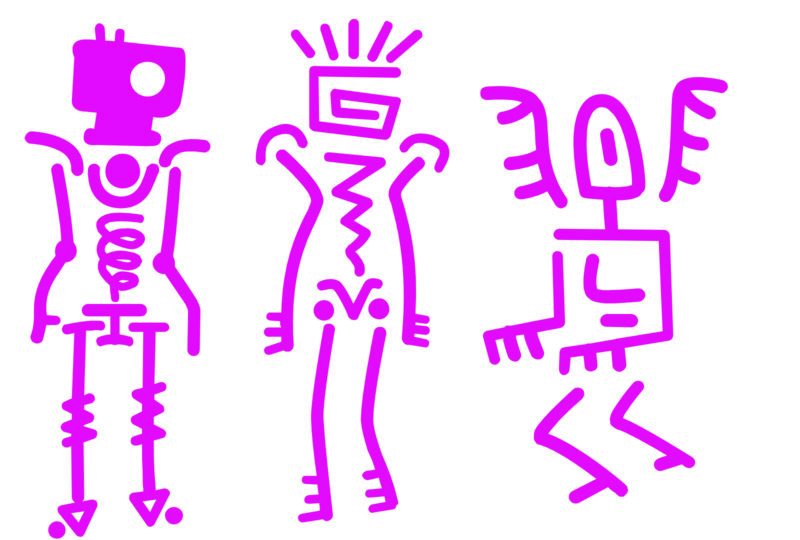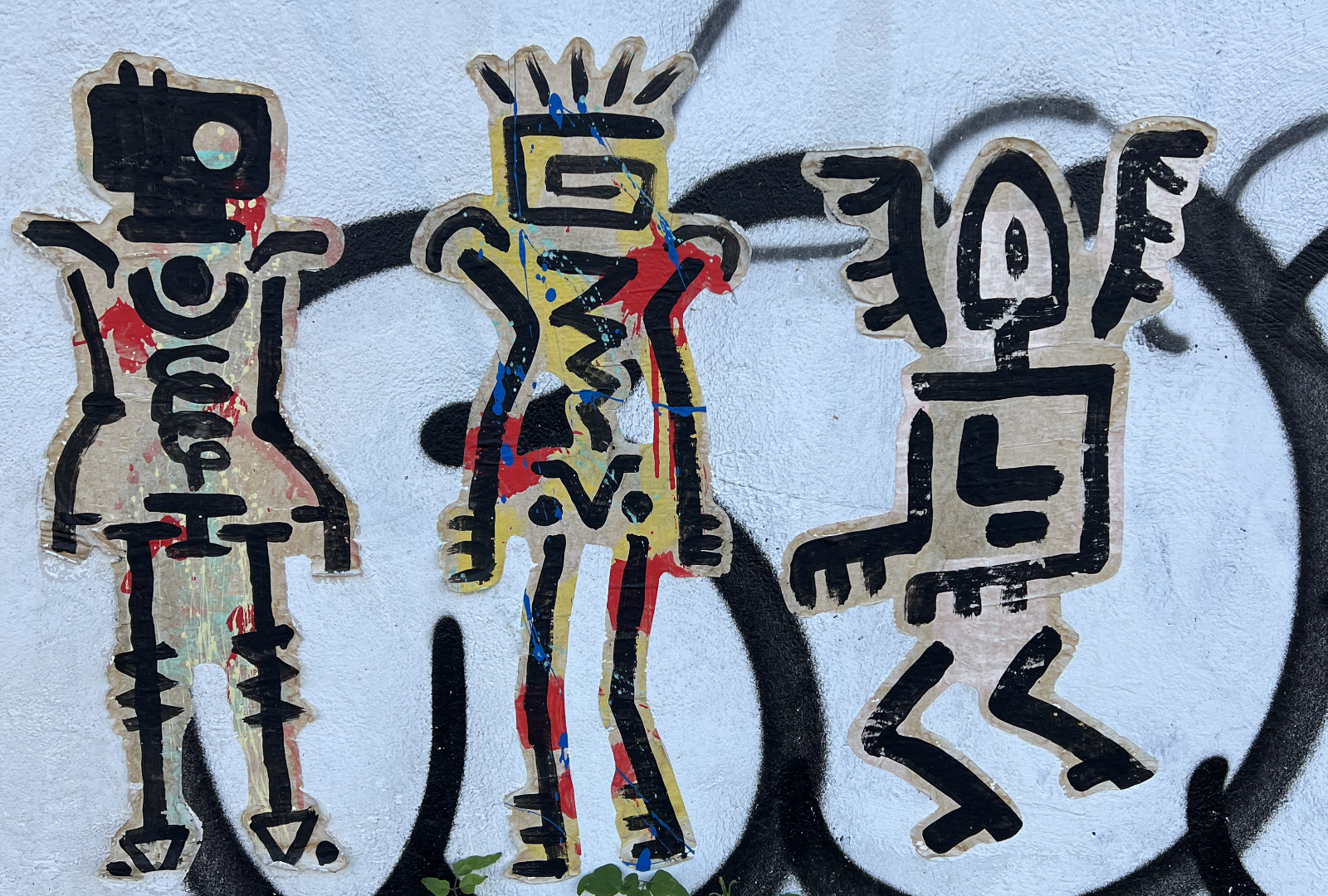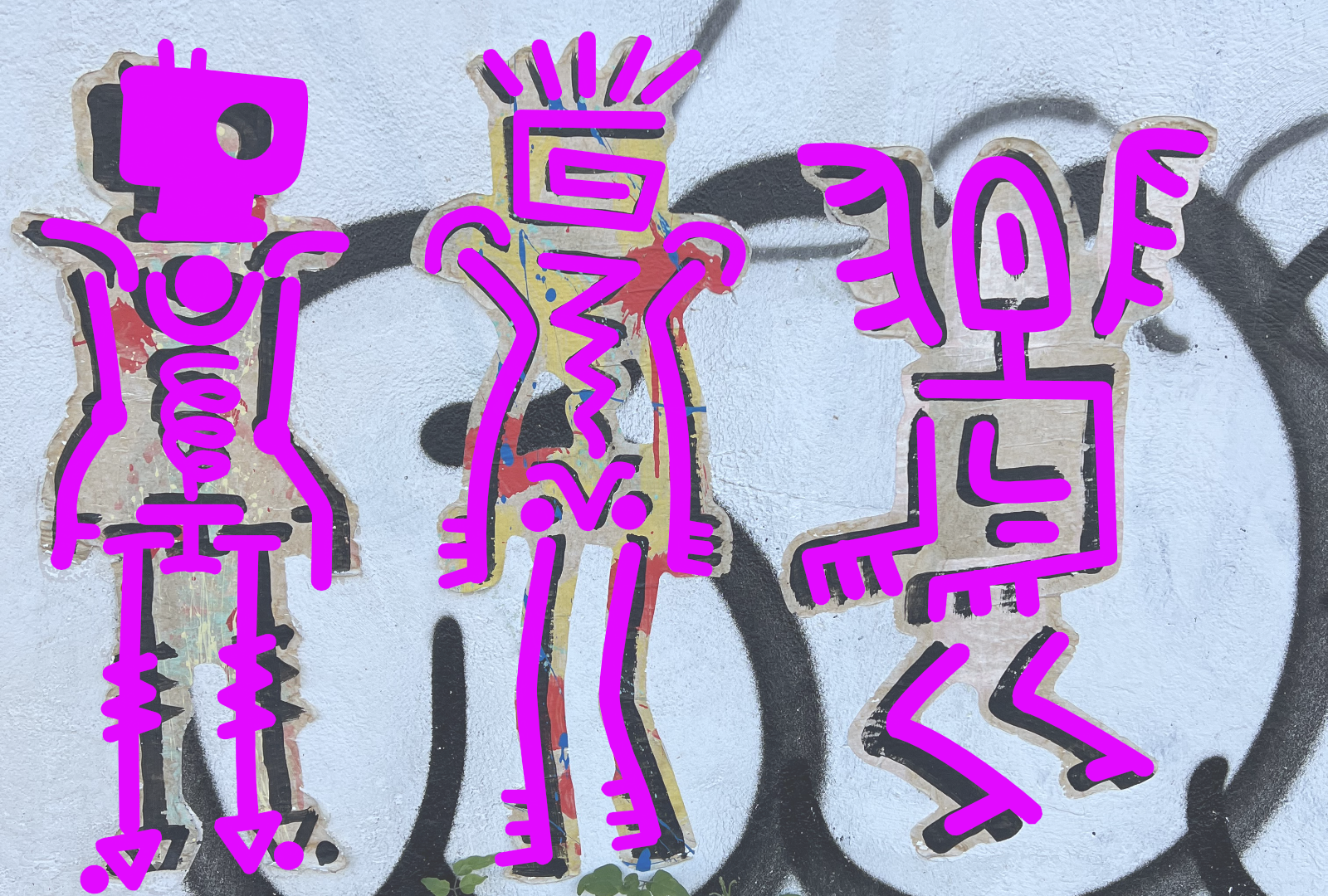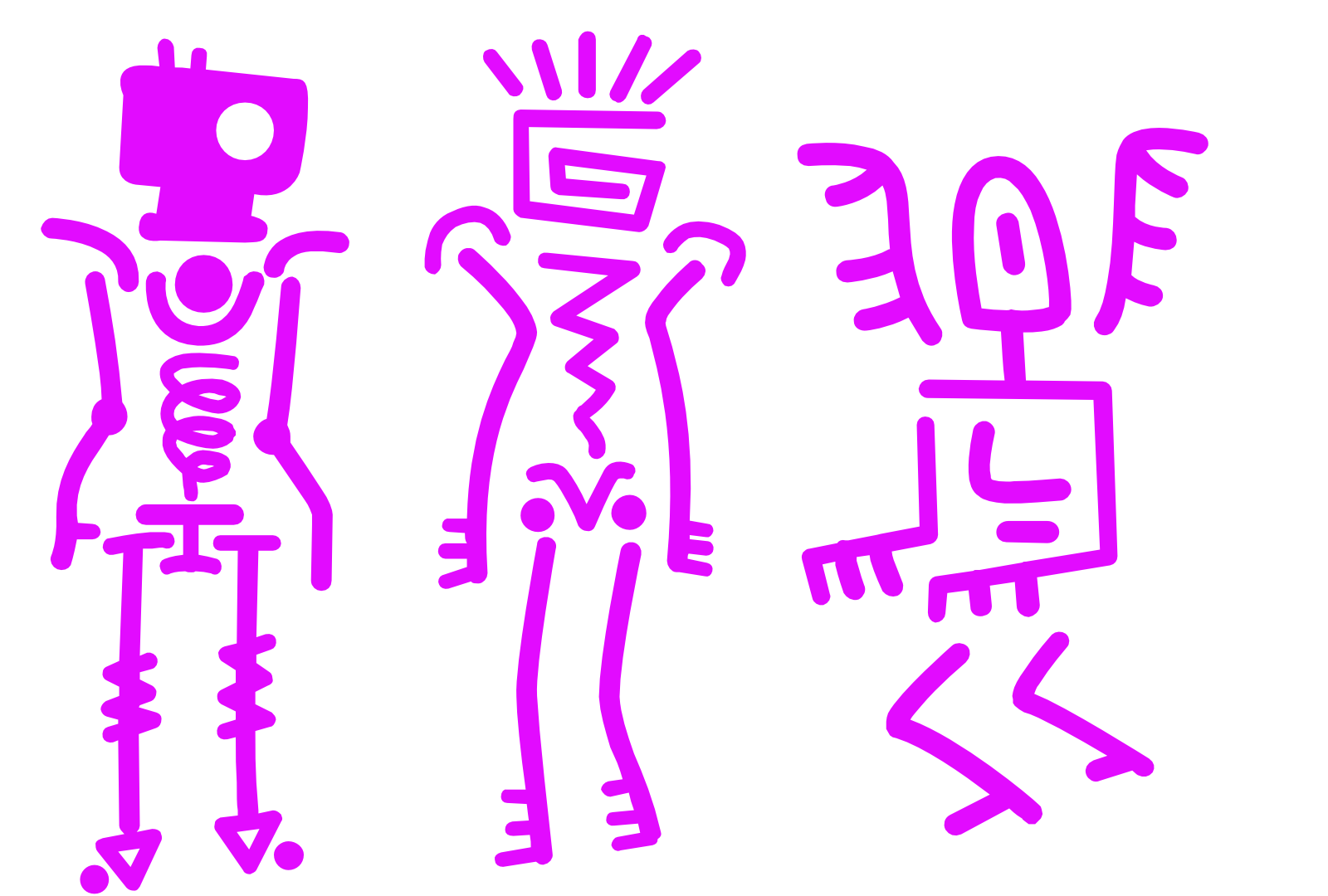
Im Teil 11 der TYPO-ECKE-Schriften geht es um lustige Strichmännchen die zu einen Dingbats-Streetartfont zusammengestellt wurden. Eine der letzten digitalisierten Männchen ist die Dreiergruppe an der Mauer beim Projekt Hanse 3. Die Ganze Geschichte der Entdeckung der Strichmännchen kann man hier --> nachlesen.
Es ist schon ein bisschen spucky oder Horror, die kleinen Figuren zu sehen. Aber es ist wahrscheinlich der erste Dresden-Graffiti-Font der existiert.